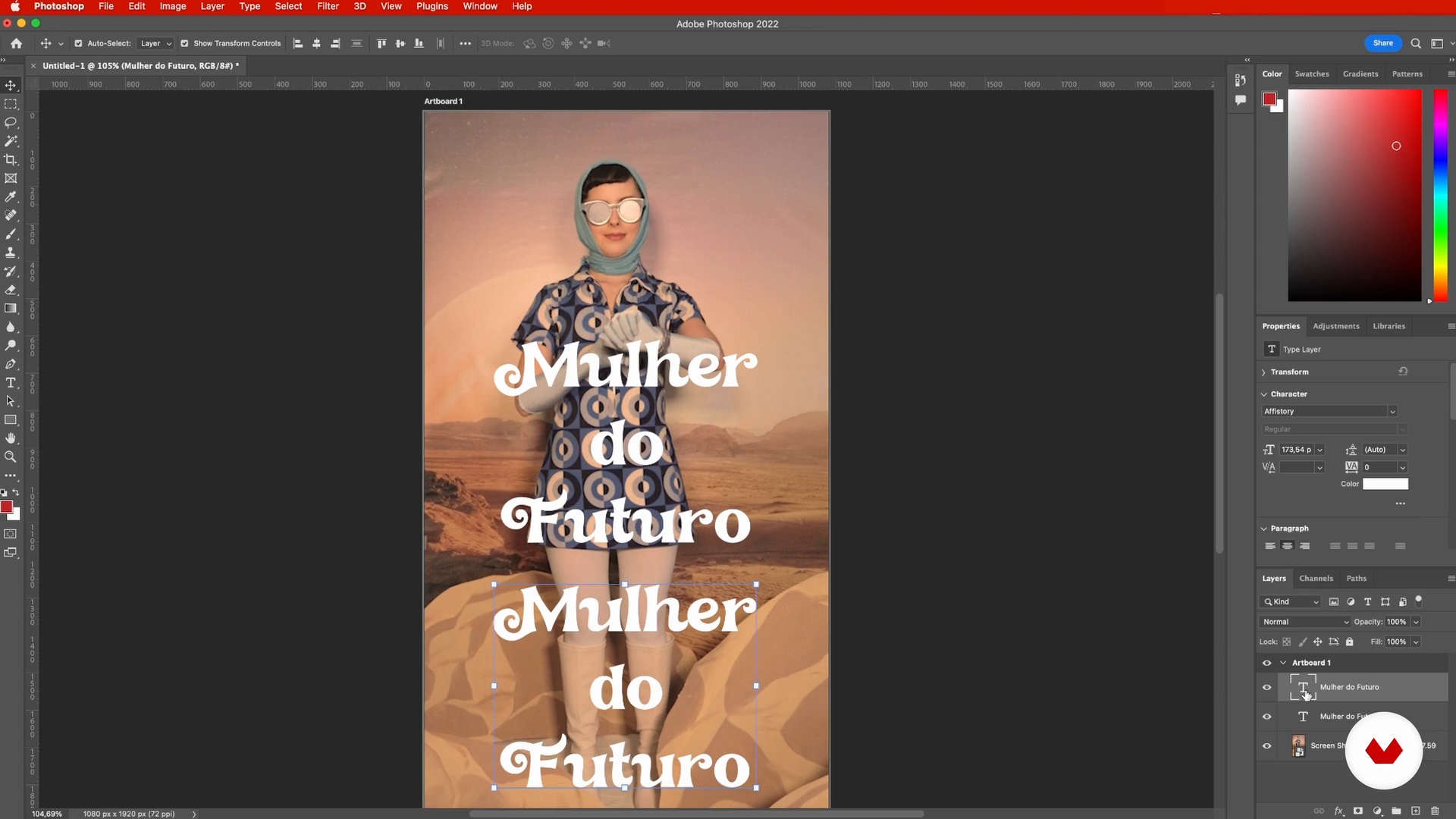
Typografia i grafika
O lekcji wideo: Typografia i grafika
Podsumowanie
“Na tych zajęciach dowiesz się, jak używać niektórych elementów projektu — typografii i ikon — do harmonijnego uzupełniania wideo. ”
Na tej lekcji wideo Letícia Ribeiro porusza temat: Typografia i grafika, która stanowi część kursu na platformie Domestika: Tworzenie efektownych niskobudżetowych treści wideo . Naucz się tworzyć zaskakujące i efektowne treści wideo mając do dyspozycji ograniczone środki, od opracowania scenariusza po końcową edycję.
“Typografia i grafika Czas na dodanie elementów graficznych naszego wideo, który może być tytułem, ramką, podpisem, ikoną. Twój film może, ale nie musi mieć tego rodzaju funkcji, ale bardzo pomagają w zrozumieniu przesłania. Jeśli chodzi o napisy, to zawsze dobrze je mieć ze względu na dostępność. a także dlatego, że wiele osób ogląda filmy w sieci społecznościowej bez dźwięku, wtedy podpis przyciągnie widza. Daj spokój? Jeden z elementów graficznych, który zamierzam zastosować w moim filmie to będzie tytuł i żeby był bardzo fajny, Poszukam czcionki pasującej do mojego tematu. Bardzo podoba ...”